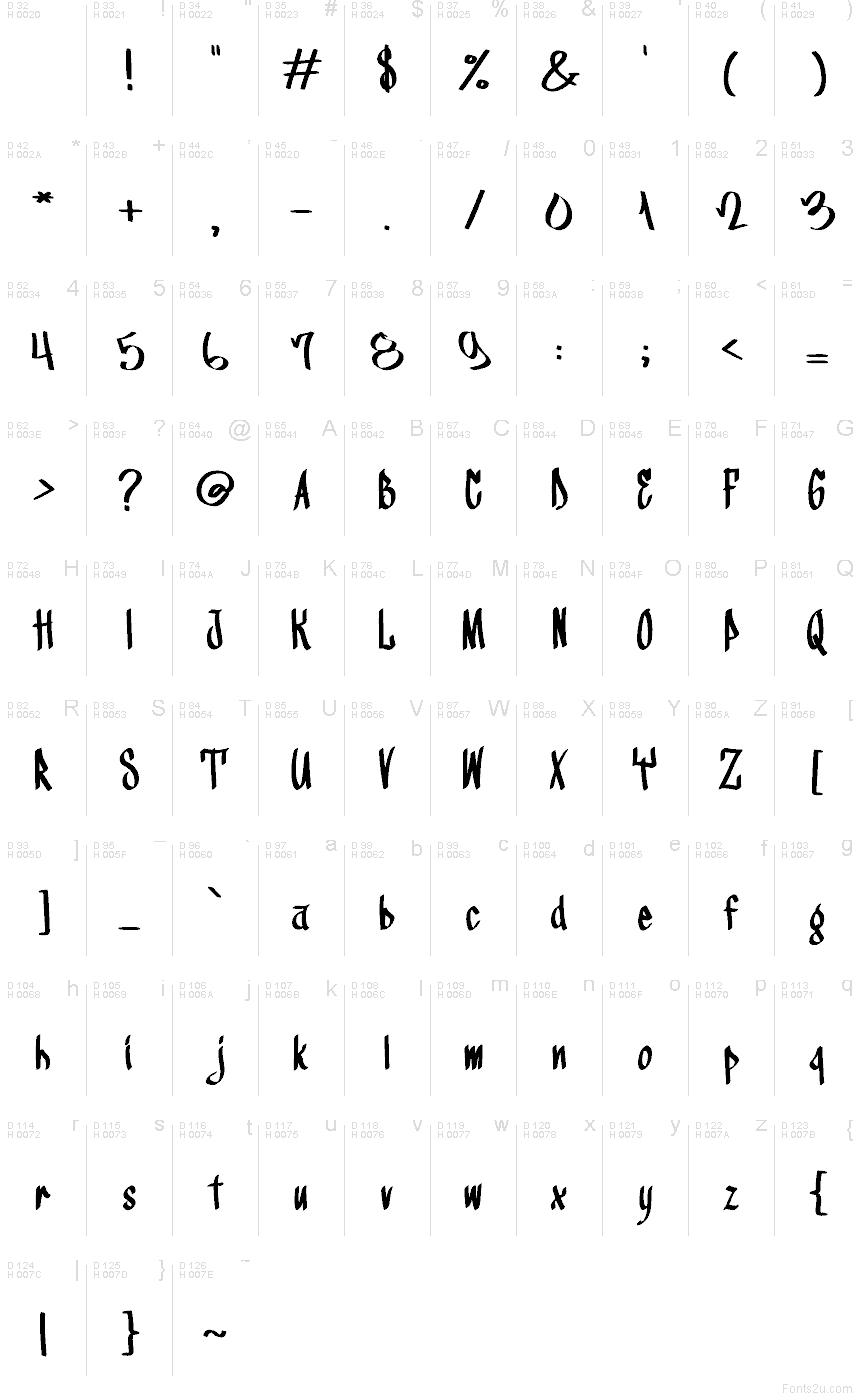
Fighter Bloom - це безкоштовний шрифт у стилі графіті з гострими, «рваними» штрихами та вузькими, загостреними формами. Літери вишикувані в динамічному, ломаному ритмі, а нерівні краї та довгі видовжені елементи надають дизайну автентичного вуличного характеру, не перетворюючи його при цьому на візуальний хаос.
Fighter Bloom чудово підходить для заголовків на плакатах, обкладинок альбомів, афіш заходів, стритвір-дизайнів та логотипів, яким потрібен грубий, міський акцент. Цей безкоштовний шрифт також вдало впишеться у спортивну графіку, музичний брендинг та виразні дописи для соцмереж, оскільки його нестандартні форми привносять яскраву рукописну індивідуальність навіть у короткі тексти.